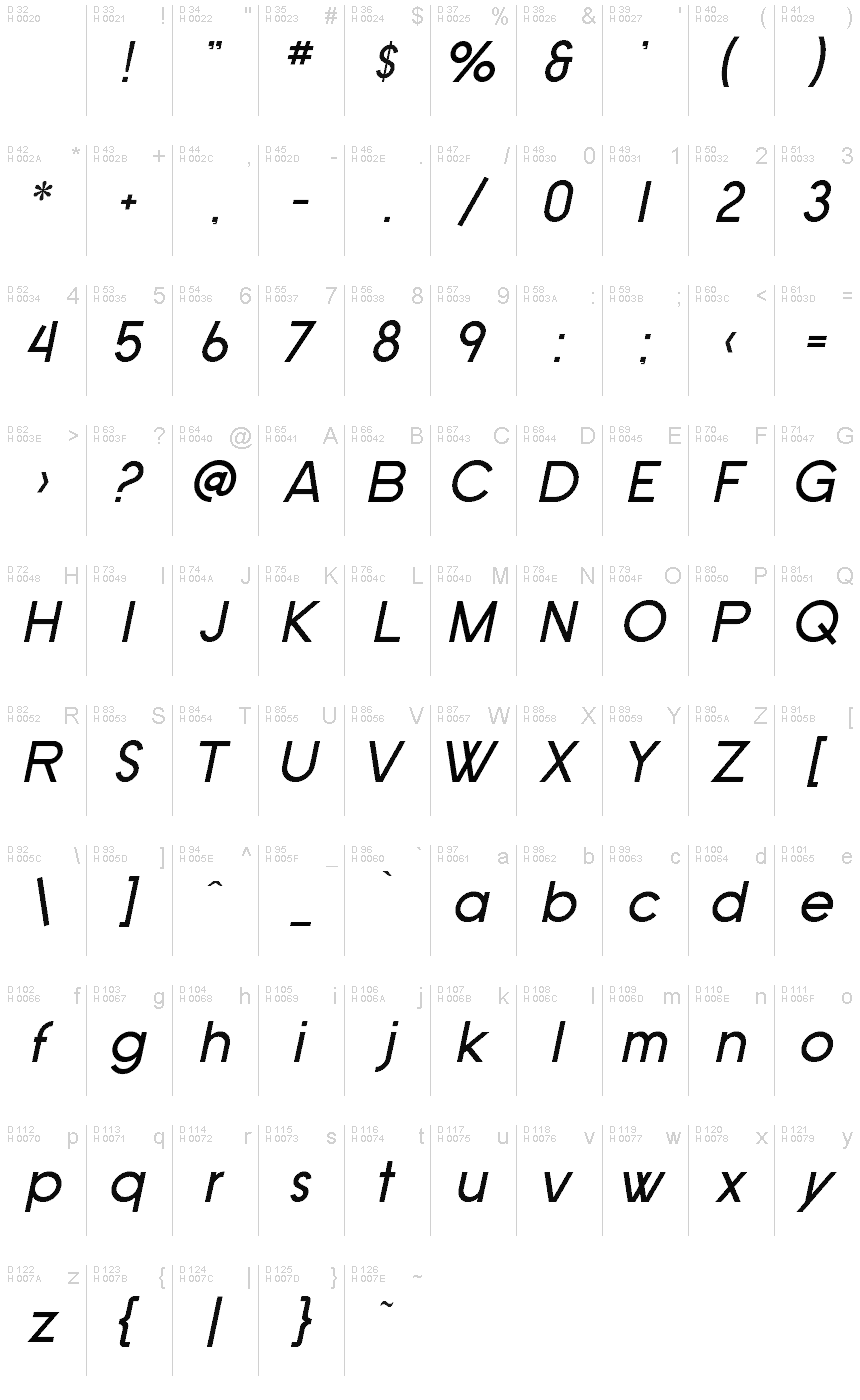
SF Old Republic Italic to wyjątkowy członek rodziny krojów SF Old Republic, starannie zaprojektowany przez ShyFonts Type Foundry. Ten bezszeryfowy font charakteryzuje się półlekką grubością, która nadaje tekstowi zwiewny, a jednocześnie zdecydowany wyraz. Kursywa dodaje całości dynamizmu, sugerując ruch i pewną siebie postawę, która przyciąga wzrok.
Estetyczny urok SF Old Republic Italic tkwi w połączeniu czystych linii z delikatnymi krzywiznami, co czyni go nowoczesnym i przystępnym wyborem dla różnorodnych projektów kreatywnych. Wszechstronność tego fontu sprawia, że doskonale sprawdza się w mediach cyfrowych, materiałach drukowanych oraz w projektach brandingowych, gdzie czytelność i charakter mają kluczowe znaczenie.
Dzięki połączeniu współczesnego stylu z klasyczną wrażliwością, SF Old Republic Italic jest doskonałym wyborem dla projektantów pragnących wprowadzić wyrafinowanie i elegancję do swoich prac, nie tracąc przy tym przejrzystości ani siły wyrazu. Niezależnie od tego, czy jest używany w tekście głównym, czy jako akcent w nagłówkach i logotypach, ten font podkreśli wizualną narrację każdego projektu.